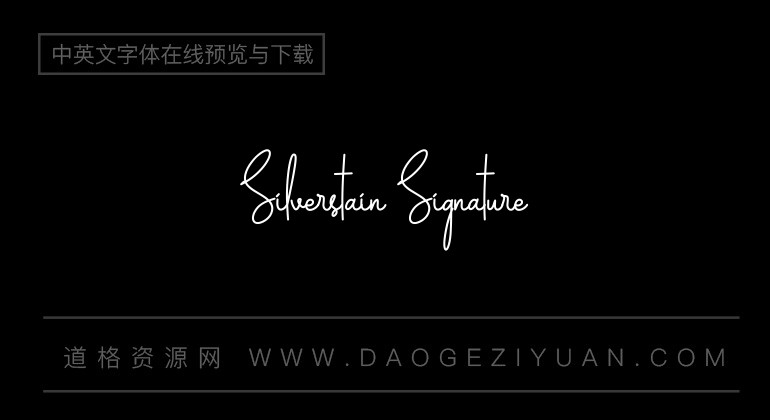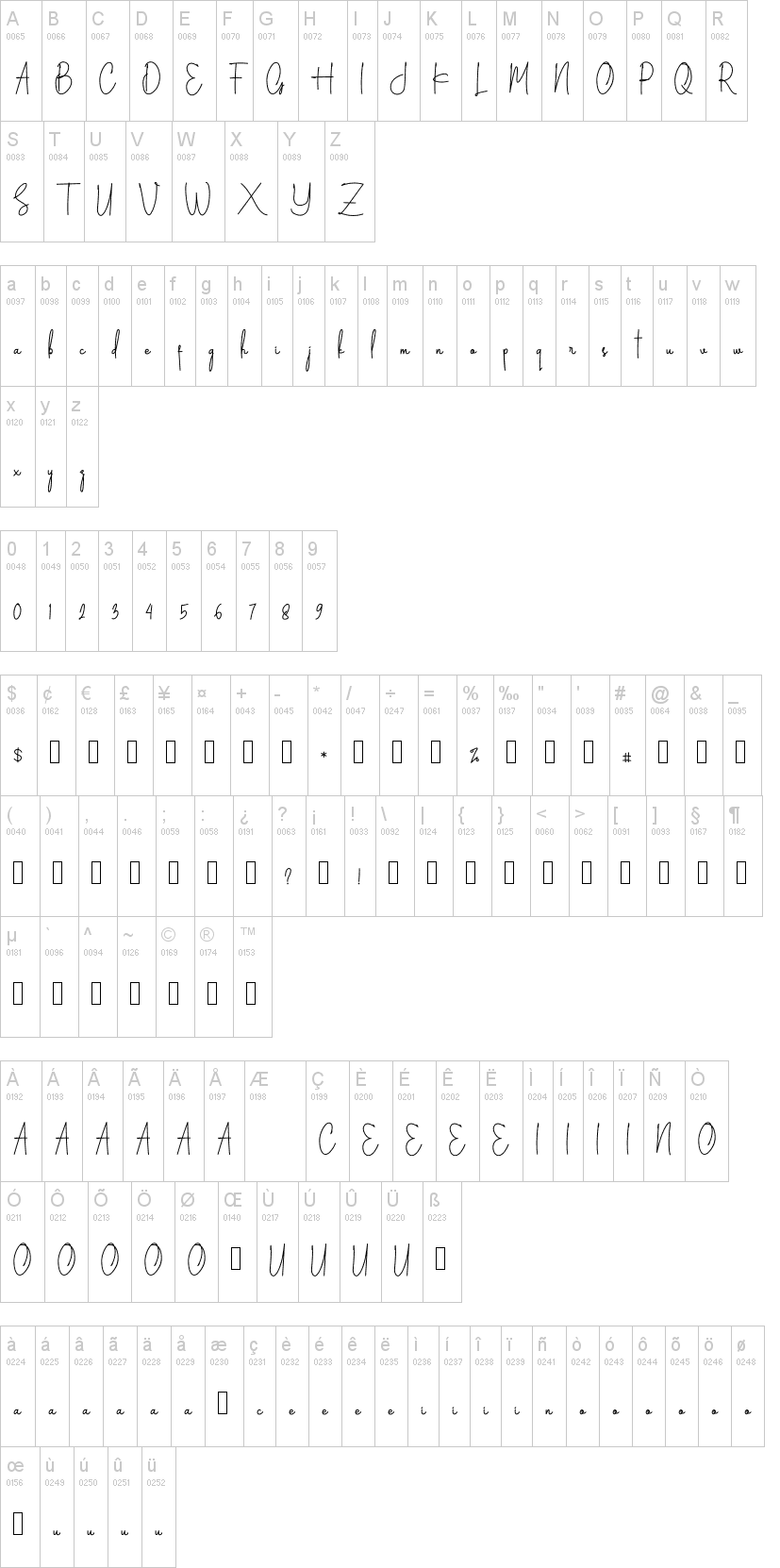
Silverstain Signature字体是一款优雅的手写体字体,它采用细腻的笔触,具有自然、灵动、柔和的特点,能够给文字增添活力和个性。它拥有超过400种不同的字形,可以满足不同的设计需求,比如标题、段落、表格、图片等。它还提供了多种字体组合,可以让设计师创造出丰富多彩的作品。内容介绍
Silverstain Signature是一款非常不错的手写艺术字体,具有很好的视觉感,适合于文化类的宣传设计、商业类品牌的广告和产品包装设计以及个性化文字排版等较多场景。